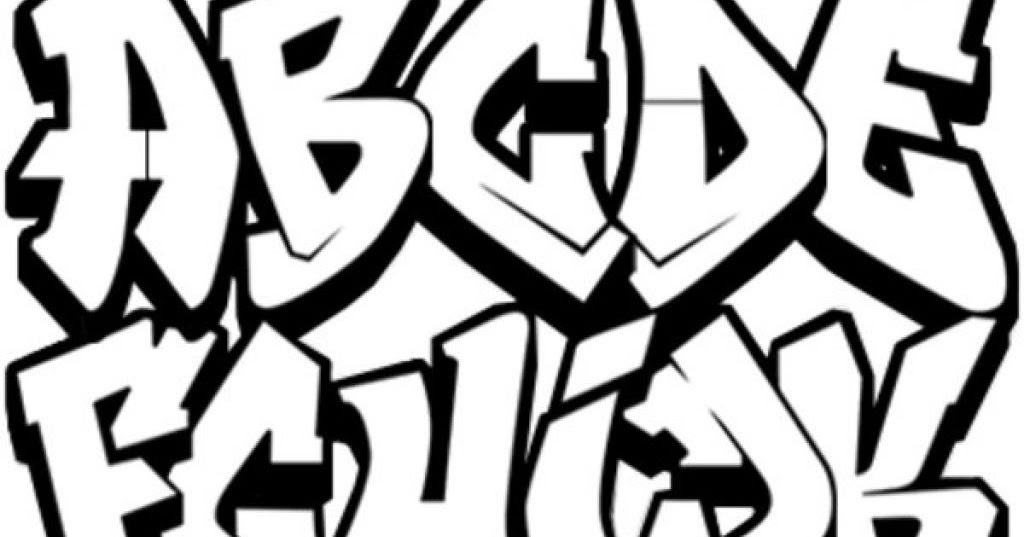
Бесплатное семейство шрифтов, созданное специально для книжного производства с нотками старинных шрифтов Garamond-esque. Crimson Text — разработан немецким дизайнером, проживающим в Торонто, Себастьяном Кош. Crimson — прекрасная альтернатива традиционному Garamond-esque, с выразительным курсивом, прекрасно сочетается с геометрическими засечками, такими как Futura или Avenir.
5. Aleo
Aleo — полукруглый с гладкой структурой шрифт, придающий нотки индивидуальности, но при этом удобочитаемый. Бесплатное семейство шрифтов, которое включает в себя шесть стилей, 3 насыщенности шрифта / weight (Light, Regular и Bold) с соответствующим курсивом.
6. Cormorant
Cormorant — это экстравагантный шрифт с засечками, наследие исторических шрифтов французского пуансониста и издателя Клода Гарамона. Был нарисован вручную Кристианом Тальманом. «Острые резкие засечки, опасно гладкие кривые», такой шрифт лучше всего использовать для заголовков или в текстах больших размеров (плакаты). Читабелен как при выводе на экран, так и в печатном виде. Cormorant поддерживает кириллицу, каждый из стилей представлен в пяти насыщенностях Light, Regular, Medium, Semibold, Bold.
Это ручная работа «Стили, современный и стиль жизни», созданная для удовлетворения потребностей вашего следующего дизайн-проекта.
Это шрифт кисти в стиле ретро, вдохновленный 80-ми годами.
Шрифт для граффити ручной работы доступен для бесплатного скачивания.
Оцените этот крутой каллиграфический шрифт!
Это рукописный экранный шрифт в стиле граффити, созданный SixAbove Studios. Прочный и разборчивый, он привносит смелые характеристики уличного искусства, чтобы внести некоторую разбивку в ваш дизайн.